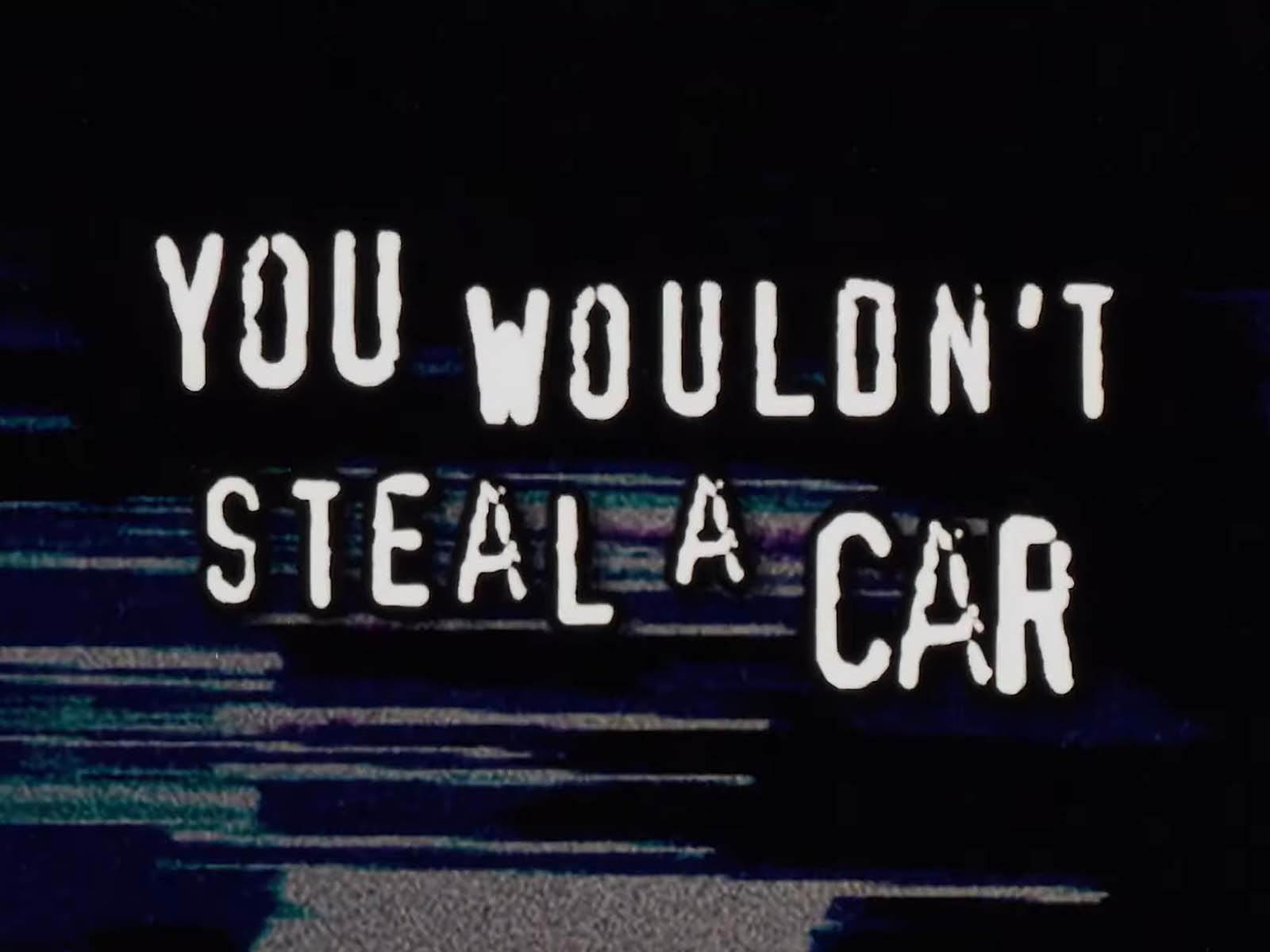
Najpoznatija kampanja za borbu protiv piraterije koristila piratizovani font: Istina isplivala nakon dve decenije
Da li biste ukrali automobil? A font?
Najpoznatija kampanja za borbu protiv piraterije iz ranih 2000-ih ponovo je u centru pažnje, i to iz ironičnih razloga. Nakon više od 20 godina, otkriveno je da je u kultnom videu koji izjednačava krađu i pirateriju upotrebljen piratizovani font.
Kampanja koja počinje rečenicom "You wouldn't steal a car" (Ne bi ukrao automobil), čiji reklamni spot je debitovao 2004. godine u bioskopima i na DVD filmovima širom sveta, imala je cilj da gledaocima objasni da je piraterija kriminal. Međutim, vrlo brzo je postala predmet brojnih šala i parodija koje traju već dve decenije.
Ono što je mnogima promaklo, a što je nedavno otkrio jedan korisnik društvene mreže Bluesky koji je analizirao jedan od originalnih PDF-ova kampanje, jeste da je kampanja koristila piratizovani font. Reč je o Xband-Rough fontu koji je nelegalna kopija licenciranog fonta FF Confidential, čiji je autor dizajner Jist van Rosum.
"Znao sam za nelegalnu kopiju svog fonta, ali nisam znao da je korišćena baš u toj kampanji", izjavio je van Rosum za Sky News. "Ta kampanja je oduvek imala pogrešan ton, što verovatno i objašnjava koliko su je ljudi ismevali. A to što je koristila piratizovani font? To je zaista dragoceno."
Organizacije koje stoje iza kampanje - britanski FACT, američka Motion Picture Association i kancelarija za intelektualnu svojinu Singapura - nisu imale mnogo da kažu na upit novinara. FACT je samo kratko poručio da kampanja potiče iz vremena pre nego što je iko od sadašnjih zaposlenih radio tamo.